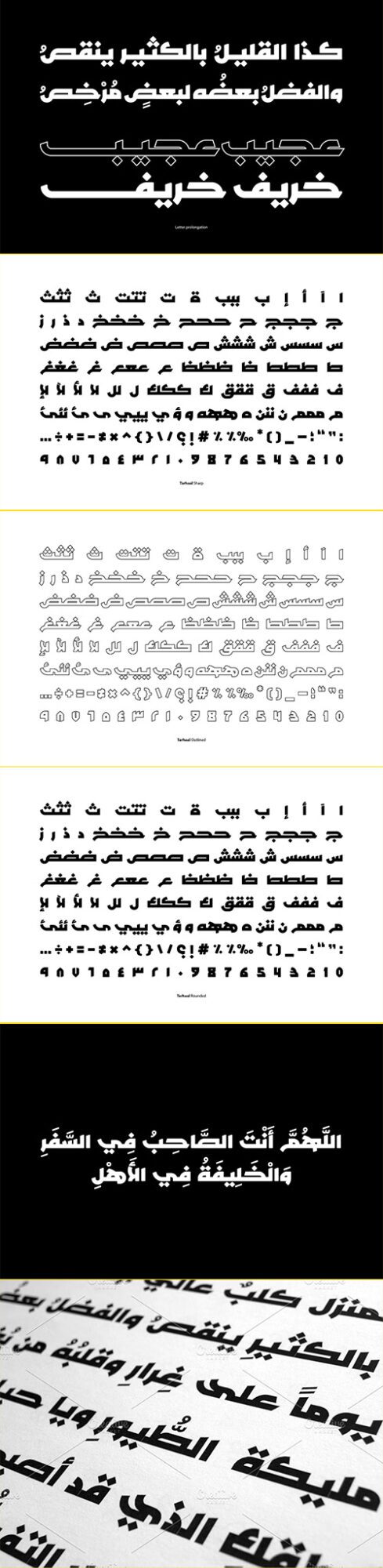
ترحال هو خط عربي مستوحى من الأنماط المرئية واللهجات من مختلف اللغات التي تستخدم النص العربي. إذا ترجمت كلمة “ترحال” من اللغة العربية، فإنها تشير إلى التراب أو البحل. ومن ثم فإن الخط لا يتميز بنمط معين من الحروف العربية، ولكنه يجمع بين أنماط متنوعة في أشكال حروف بسيطة وفريدة من نوعها.
Tarhaal is an Arabic font that is inspired by visual styles and dialects from various languages that use Arabic script. If translated from the Arabic language, the word Tarhaal indicates decampment or nomadism. Hence the font is not characterized by a specific pattern of Arabic script, but it combines varied styles in simple and unique letterforms.